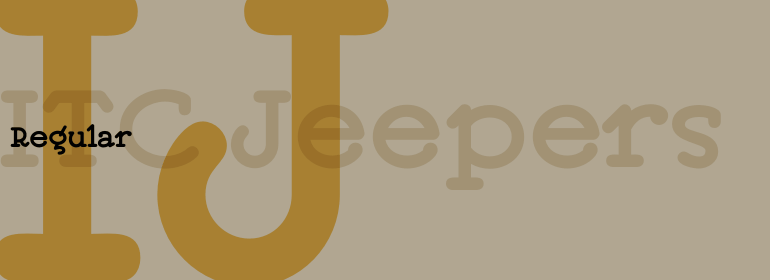
ITC Jeepers™
字体品牌: ITC(Monotype) 设计师:Curtis,Nick 字体分类:衬线体 字体属性:外文 字符集:Unicode 发布时间: 2018
设计师Nick Curtis在一张由柏林海报艺术家Paul Scheurich在20世纪20年代为德国一位书商设计的海报中找到了该字体的设计灵感。ITC Jeepers保留了Scheurich原始文字的自发性和趣味性,并加入了一些其独有的特点,其中之一就是小写字母“g”上有一个像是感叹一样的字耳。实际上,正是这种特殊字符的令人兴奋的外观才有了这个字体名称。感叹号也不甘示弱,它的表达方式更令人吃惊。
等宽、粗衬线设计具有友好的个性,非常适合于标题和其他显示用途。
Designer Nick Curtis found the inspiration for this typeface on a 1920s poster for a German bookseller, by Berlin poster artist Paul Scheurich. ITC Jeepers retains the spontaneity and playfulness of Scheurich's original lettering and adds a few surprises of its own, one being the somewhat exclamatory ear on the lowercase "g". It was, in fact, the excited look of this particular character that gave rise to the font's name. Not to be outdone, the exclamation point takes on an even more startling demeanor.
The monoweight, slab serif design has a friendly personality, perfect for headlines and other display uses.